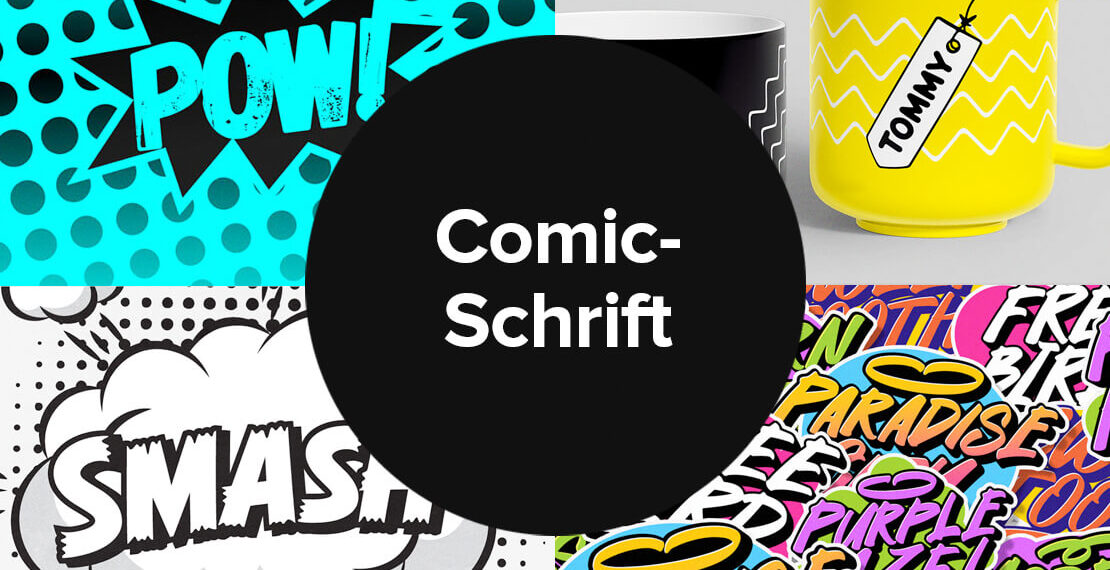
❤ Comic-Schrift, Kostenlose Fonts für Sprechblasen und Co.
Comic-Schrift ist entscheidend, damit Comic-Hefte, Cartoons oder Graphic Novels lebendig werden. Eine Auswahl mit frischen und kostenlosen Comic-Schriftarten für Sprechblasen, Schriftzüge, Gedankenblasen und mehr kommt hier.
Evolution und Vielfalt der Comic-Schriften
Comic-HeftDie Entwicklung der Comic-Schrift spiegelt die dynamische Geschichte des Comics selbst wider. Von Graphic Novels über Mangas bis hin zu traditionellen Comic-Heften und Cartoons – jedes Format hat seine eigene visuelle Sprache entwickelt, die durch die passende Comic-Schrift beeinflusst wird. Die Wahl der richtigen Comic-Schrift ist entscheidend, um die einzigartige Atmosphäre und den Charakter eines jeden Werks hervorzuheben.
Lange Zeit schien die Auswahl an Comic-Schriftarten begrenzt, mit Comic Sans als einer der bekanntesten und zugleich kontroversesten Optionen. Diese Schriftart wurde oft kritisiert und übermäßig eingesetzt, was ihre Wirksamkeit in kreativen Projekten minderte. Mittlerweile gibt es unzählige Comic-Schriftarten, die dabei helfen können, um beispielsweise Fotos wie Comics wirken zu lassen, Comic-Serien in Szene zu setzen oder cartoonhafte Elemente – beispielsweise im Game Design – darstellen zu können. Hier kommt eine Auswahl mit Comic-Schriften, die es zum Downloaden gibt.
Comic Hero
Das Kereatype Studio hat eine clevere Comic-Schrift mit drei Schnitten gestaltet. Neben dem regulären Font, gibt es auch Varianten für Umrandung und Schatten, die sich miteinander kombinieren lassen. Die Schnitte „Outline“ und „Shadow“ gibt es kostenlos bei Gumroad zum Downloaden.
Die Comic-Schrift „Comic Hero“ besteht aus drei Fonts zum Kombinieren. (© Abb.: Kereatype Studio – kereatype.gumroad.com/l/comichero)
Panic Attack
Aus der Feder von Ferry Ardana Putra kommt eine verspielt wirkende Comic-Schriftart. Die Display-Schrift bietet sowohl eine reguläre als auch eine extrudierte Version, die die Möglichkeit bietet, einen dreidimensionaler Effekt hinzuzufügen. Weitere Sonderzeichen bringen Schwung ins Schriftbild.
Comic-Font für Schilder, Poster und Co. (© Abb.: Ferry Ardana Putra – behance.net/gallery/189157969/FREE-DOWNLOAD-PANIC-ATTACK-PLAYFUL-COMIC-FONT)
Neue Comic
Neue Comic ist eine abgerundete Schriftart, die von Unio Creative Solutions mit dem Ziel entwickelt wurde, die Balance zwischen Verspieltheit und Praktikabilität in der Typografie neu zu definieren. Sie nutzt abgerundete Ästhetik, um die Informationsaufnahme und Lesbarkeit zu verbessern und bietet ein rhythmisches Design. Inspiriert von Schriftarten in Comic-Büchern, greift Neue Comic den Charme der 90er Jahre auf.
Durch ihre Rundungen kommt diese Comic-Schrift sympathisch und verspielt herüber. (© Abb.: Unio Creative Solutions – behance.net/gallery/187013377/Neue-Comic-freebie-included)
Mit sieben Schnitten und entsprechenden Italics sowie einer variablen Version bietet Neue Comic eine flexible und ansprechende Option für Kreative, die Spaß und Eleganz in ihren Projekten vereinen möchten. Den Heavy-Schnitt gibt es kostenlos zum Downloaden.
Planet Comic Font
Diese freundlich wirkende Comic-Schrift von Khurasan lässt sich für private und kommerzielle Zwecke gleichermaßen verwenden. Der Download enhält die Opentype- und TrueType-Version des Fonts.
Khurasan hat eine freundlich wirkende Comic-Schrift gestaltet. (© Abb.: Khurasan – behance.net/gallery/173575445/Planet-Comic-Font-free-for-commercial-use)
Honey Type Comic-Schrift
Entworfen von Rebecca Harding für den Web-Comic Honey Crab, spiegelt diese Schriftart die persönliche Handschrift der Illustratorin wider. Verfügbar in zwei Varianten, kann Honey Type kostenlos auf Gumroad heruntergeladen werden, um Geschichten Charakter zu verleihen.
Diese Comic-Schrift basiert auf einer Handschrift und wurde für einen Web-Comic gestaltet. (© Abb.: Crab Artist – gumroad.com/honeycrab)
HVD Comic Serif – für Comic-Schriftzüge und mehr
Als sympathische Alternative zu Comic Sans von Hannes von Döhren kreiert, bietet HVD Comic Serif mit seinen Serifen eine ansprechende Optik. Diese „coole Alternative zu Comic Sans“ ist kostenlos auf der Website des Designers als kostenloser Download erhältlich.